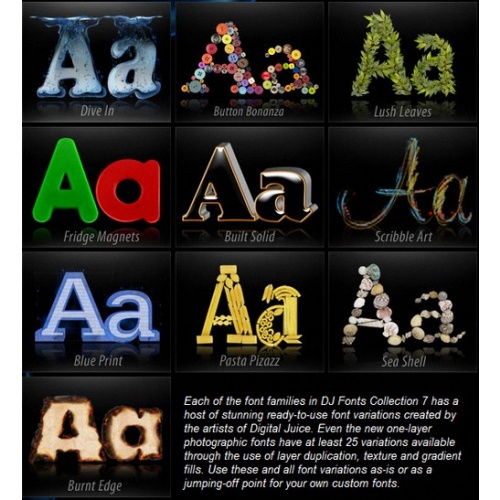
7, 8, 9, 10 — это новые коллекции шрифтов, которые содержат соответственно 10, 13 и 2 по 11 уникальных, совершенно новых семейств шрифтов и более чем 500 новых DJ-шрифтов. Седьмая, Восьмая, Девятая и Десятая коллекции — это больше, чем просто еще четыре сборника шрифтов, половина этих коллекций состоит из уникальных фотографических шрифтов. Эти шрифты действуют подобно любым из предыдущих семейств шрифтов, с тем исключением, что они основаны на фотографиях высокого разрешения, а не на иллюстрациях или 3D.
Каждая группа DJ-шрифтов в этих коллекциях является результатом сотни часов кропотливой работы иллюстраторов Digital Juice.
— Седьмая коллекция содержит 10 уникальных DJ-семейств шрифтов, более 500 готовых к использованию стандартных DJ-шрифтов, а также неограниченное количество возможностей настроить и сделать свой собственный DJ-шрифт.
— Восьмая коллекция содержит 13 уникальных DJ-семейств шрифтов — 8 фотографических и 5 иллюстрированных, более 500 готовых к использованию стандартных DJ-шрифтов, а также неограниченное количество возможностей настроить и сделать свой собственный DJ-шрифт.
— Девятая коллекция содержит 11 уникальных DJ-семейств шрифтов — 8 новых фотографических и 5 иллюстрированных, более 400 вариантов готовых к использованию стандартных DJ-шрифтов, а также неограниченное количество возможностей настроить и сделать свой собственный DJ-шрифт.
— Десятая коллекция содержит 11 уникальных DJ-семейств шрифтов — 3 новых фотографических и 4 иллюстрированных, более 500 вариантов готовых к использованию стандартных DJ-шрифтов, а также неограниченное количество возможностей настроить и сделать свой собственный DJ-шрифт.
Digital Juice Fonts – не являются традиционными шрифтами, а простыми словами DJ Fonts – расположенные на слоях графические шрифты, их можно модифицировать как свойства любого текста (размер шрифта, кернинг и т.п.) в приложении Juicer. Все шрифты легко редактируются, выводятся в различных форматах для импорта в другие графические программы, например Adobe Photoshop, Adobe Illustrator, Adobe Premiere, After Effects, Sony Vegas, Apple Motion 3, и т.п…
Digital Juice Fonts: Collection 7, 8 & 9 is more than just another volumes of fonts, over half of this collections is made up of hand-assembled, highly unique photographic typefaces. These fonts act much like any of our previous font families in the Juicer, with the exception that they are based on high resolution photography, not illustration or 3D rendered art.
Digital Juice Fonts Collection Seven:
Each of the font families in DJ Fonts Collection 7 has a host of stunning ready-to-use font variations created by the artists of Digital Juice. Even the new one-layer photographic fonts have at least 25 variations available through the use of layer duplication, texture and gradient fills. Use these and all font variations as-is or as a jumping-off point for your own custom fonts.
Overall, Collection Seven contains 10 unique DJ Font Families — 5 photographic and 5 illustrated, over 500 ready-to-use DJ Standard Fonts, and an unlimited stream of future font customizations through our My DJ Font and Community DJ Font features.
Digital Juice Fonts Collection 7 contains 5 new fonts that started out as super high resolution photographs. Each letter in the character set was hand-assembled, shot and then painstakingly cut out to form these fonts. Because they are photographic in origin they have an unsurpassed level of realism you just won’t find anywhere else. And, just like the illustrated fonts in the volume, they can be customized, arranged and rendered from the Juicer. You also get the system font they were based on, just as you do with our other DJ Fonts.
Features:
— 10 Brand New Font Families
— More than 500 ready-to-use Standard DJ Fonts variations
— 5 Illustrated & 5 All-New Photographic Fonts
— 5-10 layers per illustrated font
— Each font glyph designed at a high resolution of approx. 2000 x 2000 pixels for maximum flexibility in uses
— Most fonts contain a full 152-character glyph set
Digital Juice Fonts Collection Eight:
Each of the font families in DJ Fonts Collection 8 has a host of stunning ready-to-use font variations created by the artists of Digital Juice. Even the new one-layer photographic fonts have at least 25 variations available through the use of layer duplication, texture and gradient fills. Use these and all font variations
Overall, Collection Eight contains 13 unique DJ Font Families — 8 photographic and 5 illustrated, over 500 ready-to-use DJ Standard Fonts, and an unlimited stream of future font customizations through our My DJ Font and Community DJ Font features.
— Most fonts contain a full 152-character glyph set